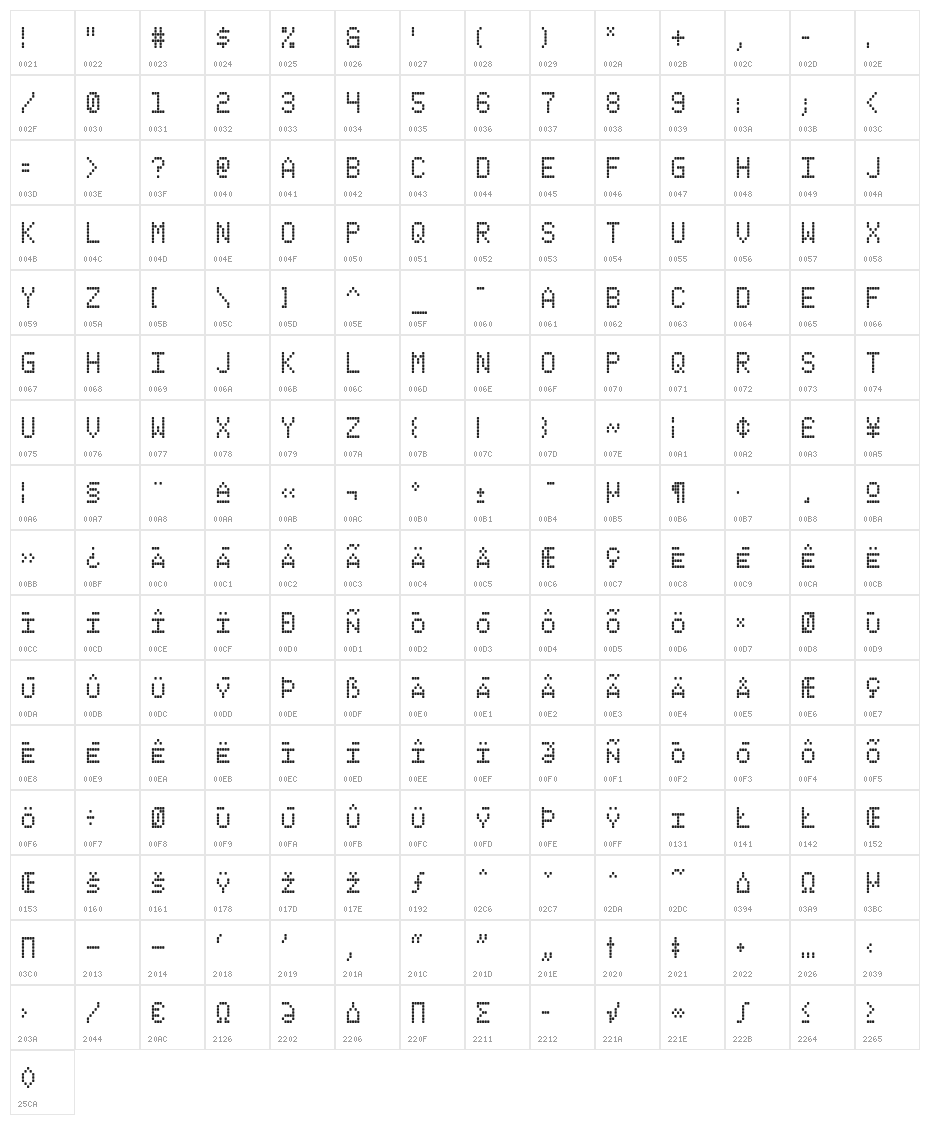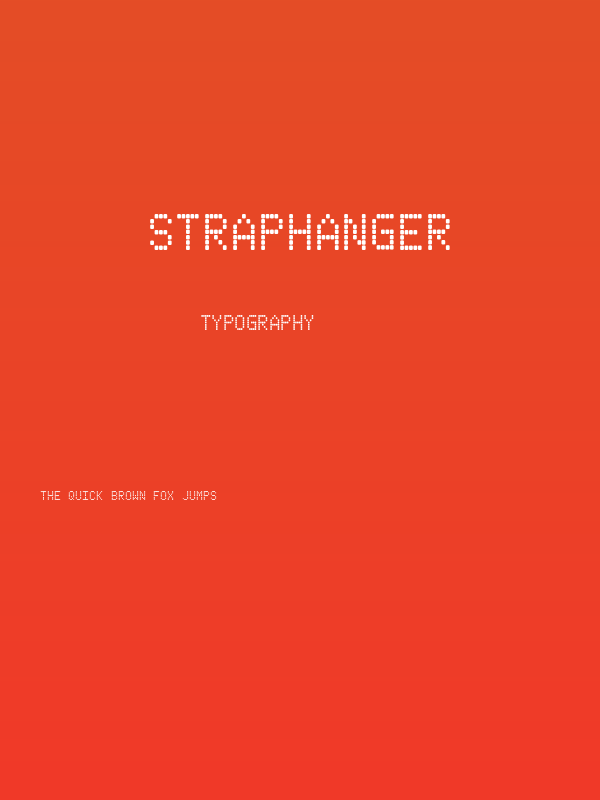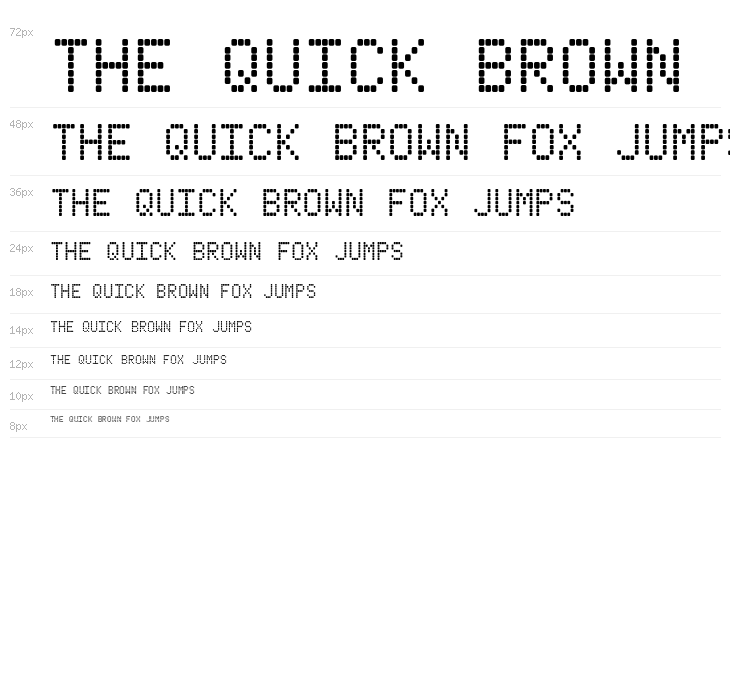
Straphanger Font
| समग्र शैली | Retro, Futuristic |
| उपयोग का मामला | Headlines, Logos, Digital Displays |
| सुझाए गए प्रोजेक्ट | Ideal for digital displays, retro-themed designs, tech-related branding, and creative posters. |